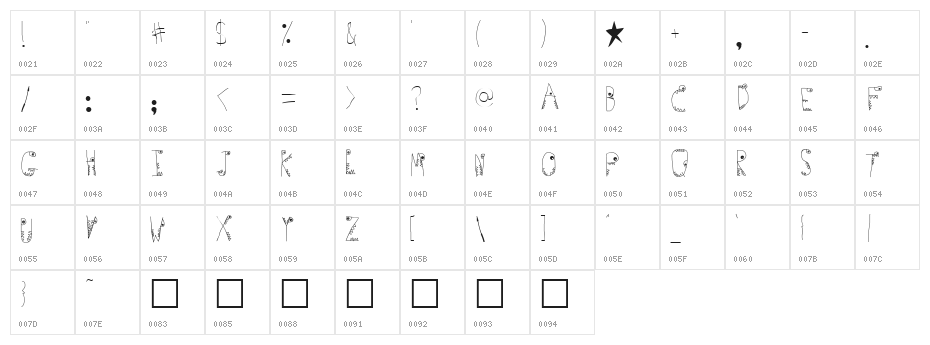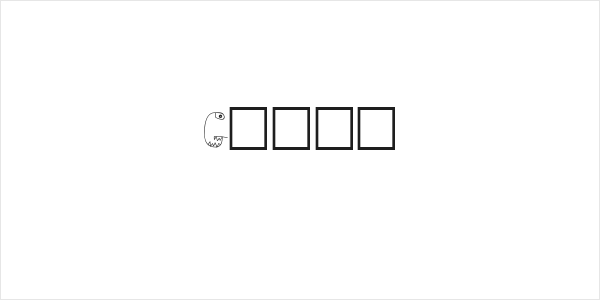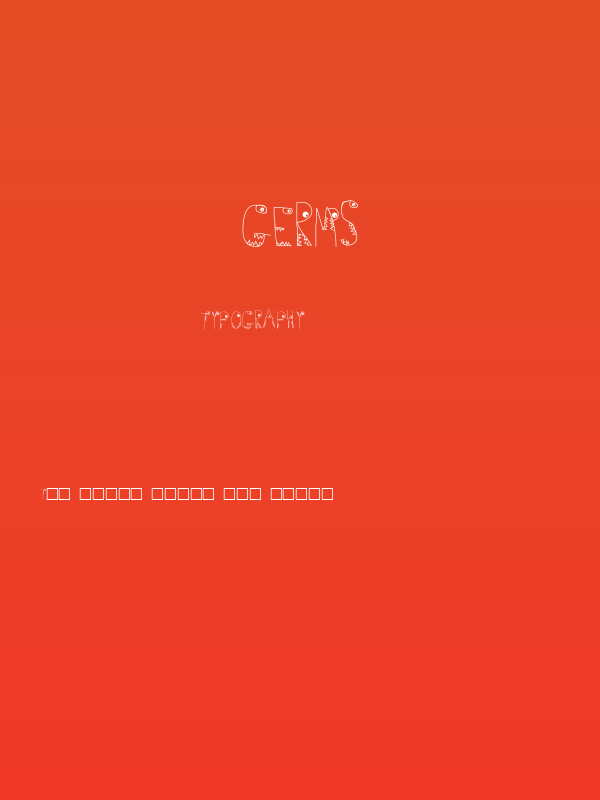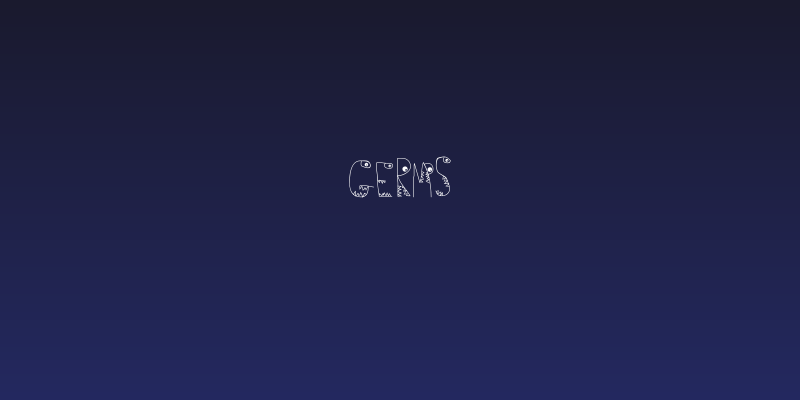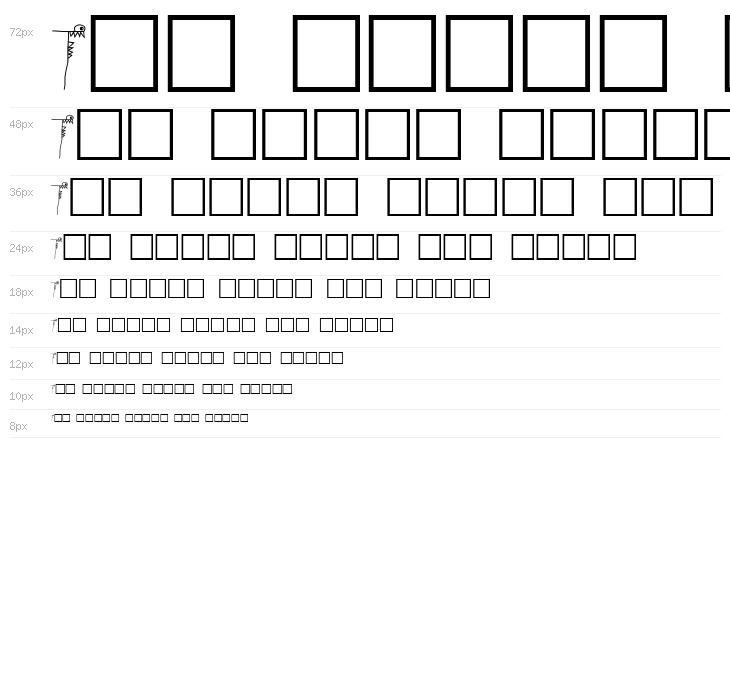
Germs Font
| समग्र शैली | Whimsical, Playful |
| उपयोग का मामला | Headlines, Logos, Posters |
| सुझाए गए प्रोजेक्ट | Ideal for children's books, Halloween-themed designs, playful posters, and creative branding projects. |